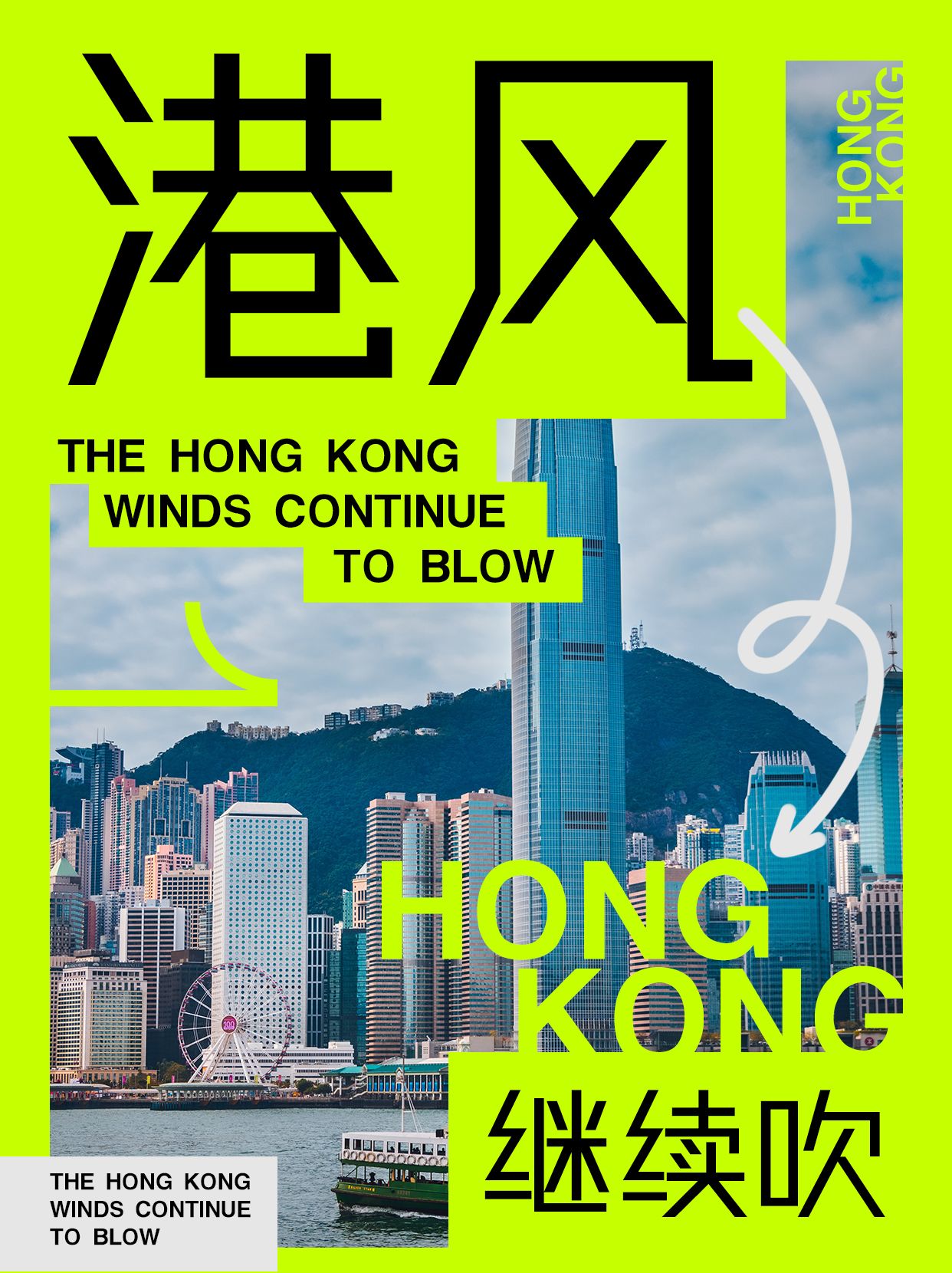
黑体可说是目前使用最广泛的字体,广义上说,没有衬线的字体通常都可以称为黑体,黑体是对字面呈正方形、笔画横平竖直且等粗类字体的统称。随着制字技术的精进,黑体具有了不同字重和宽窄的字形,让黑体应用领域更为广泛,无论标题、内文还是注释都可以胜任。
简洁和规矩的黑体在气质上没有太大的个性,它适用的范围比较大,可塑性很强,通过字形的变化,可以表现出不同的气质。
造字侠香港硬黑简 常规,一款直线黑体,从建筑精度中提取灵感,采用无弯曲的硬哥特式笔画以及横竖视觉等粗的干练简约,使字体呈现机械性的建筑美感;尖锐的折角及交叉的钝角笔画组合,宣誓字体锐利的个性主张;完美的几何图形构建骨架设计,使字体有严苛的精确,又有极具力量感的稳固。精简的内部空间、灵活的结构处理,整体视觉非常刚硬锐利的现代黑体。